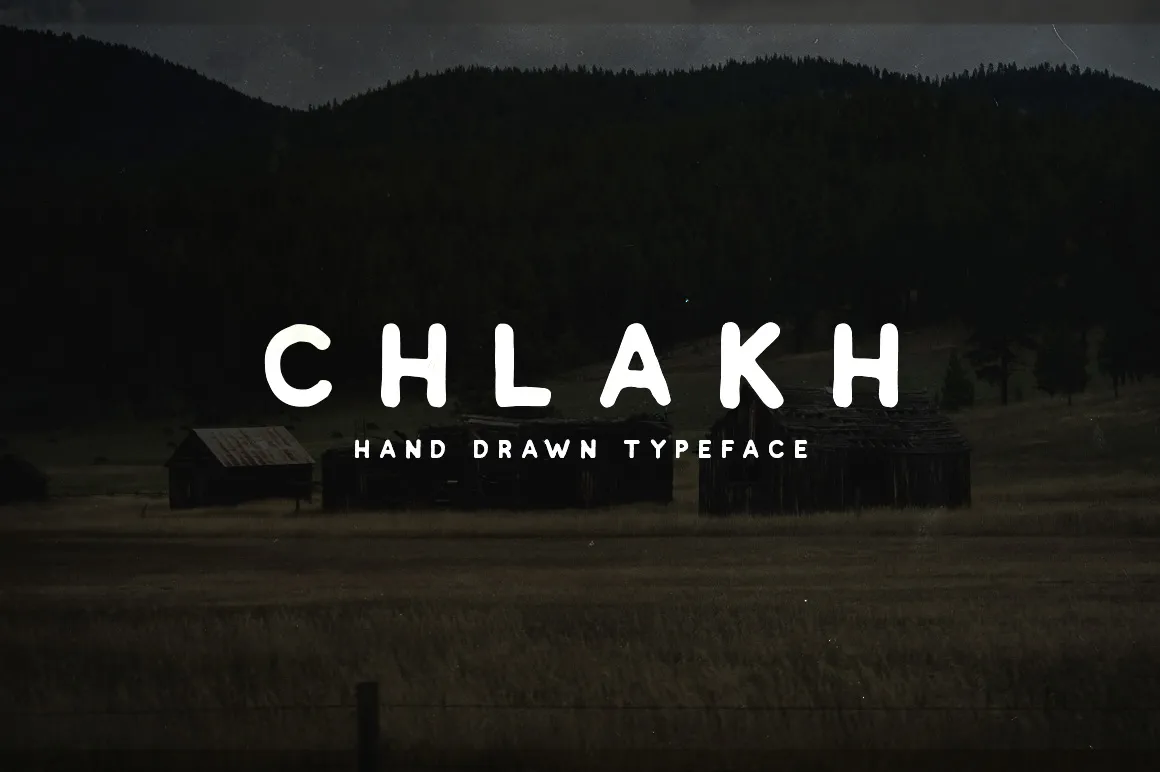
Chlakh Typeface – Download Grátis
A fonte ‘Chlakh Typeface’ é perfeita para criar logotipos retrô, badges, rótulos, mas seu uso não se limita a isso. É ideal também para aplicar em camisetas personalizadas, embalagens de alimentos, cartões de negócios, folhetos e panfletos, anúncios, menus de restaurantes, sinais e até mesmo na criação de tipografias customizadas ou citações. Com ‘Chlakh’, você encontra uma fonte versátil que se adapta a diferentes demandas do design gráfico, tornando-a uma escolha ideal para qualquer projeto visual que busque um estilo retrô elegante e autêntico. Não importa o formato do seu trabalho, Chlakh é capaz de dar vida ao seu design com sua tipografia minimalista mas atemporal.